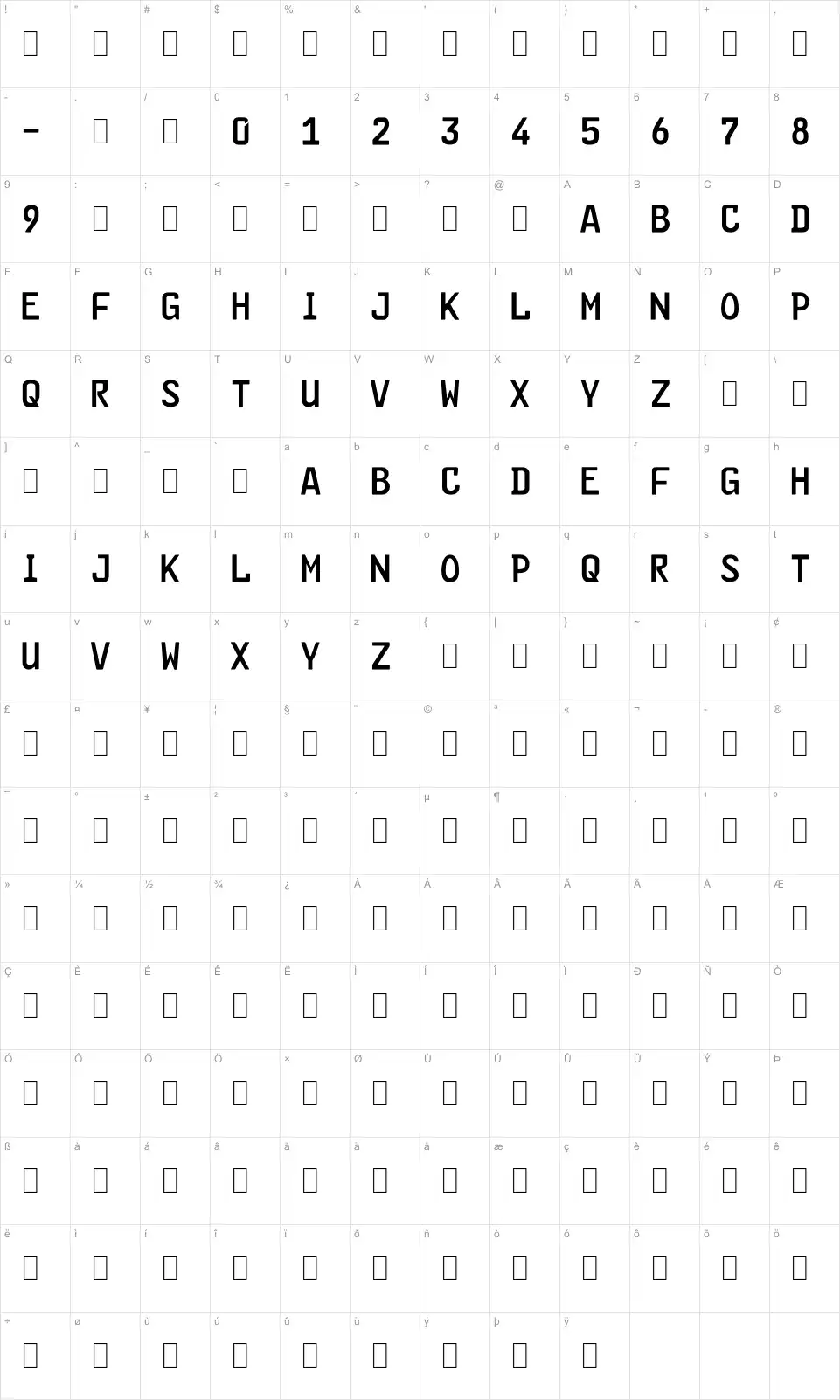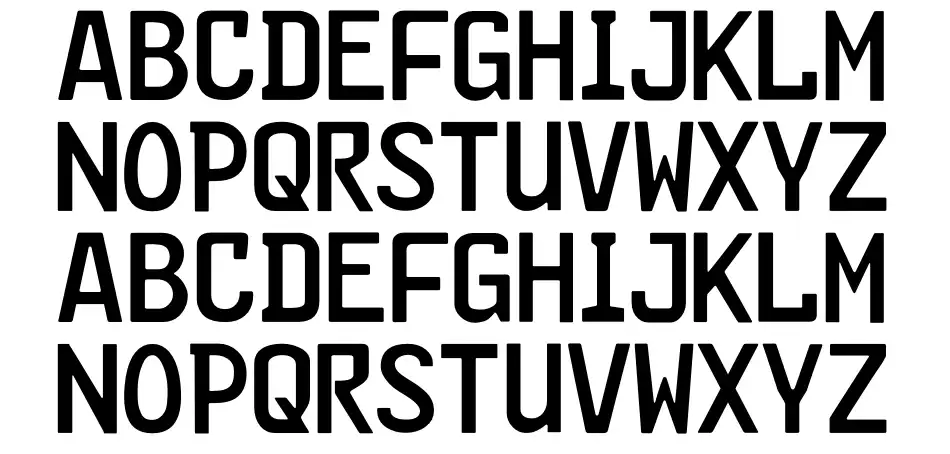
FE-Font
A FE-Font é uma fonte de categoria Basic, ideal para gráficos e textos mais simples. Desenvolvida para designers que buscam um estilo limpo e funcional, esta fonte vem em formato TTF, permitindo sua utilização em uma variedade de plataformas digitais. Se você está procurando por uma fonte básica para projetos básicos, a FE-Font pode ser uma ótima escolha. Esta fonte foi adicionada à nossa plataforma em 12 de julho de 2022 e já foi baixada 1981 vezes, mostrando seu valor e popularidade. Em apenas 8 KB, a fonte é leve e perfeita para usos em projetos de design semelhantes a blogs, páginas de recursos gráficos ou sites de design. Teste-a em seu próximo projeto e veja como ela se destaca em sua interface de design.